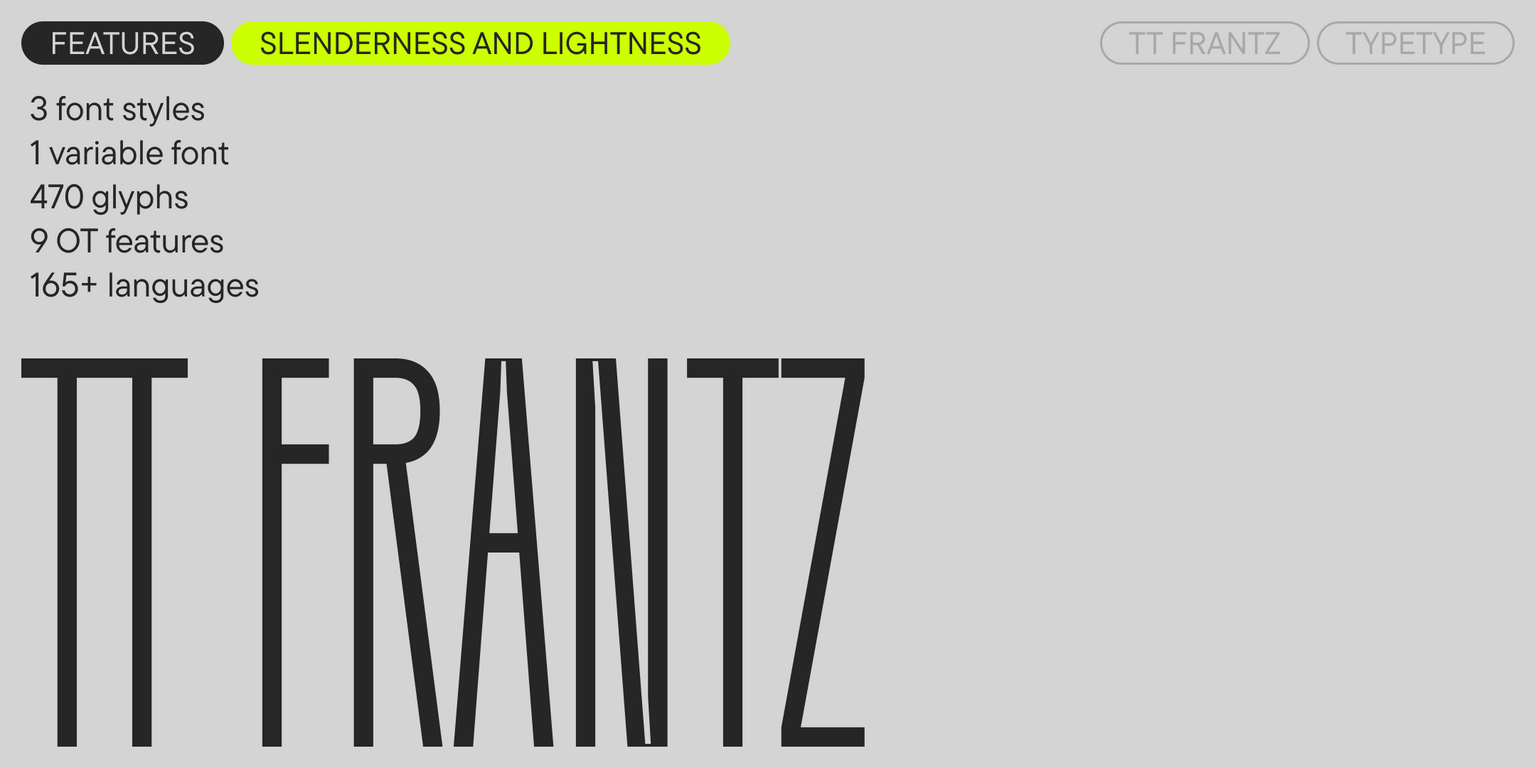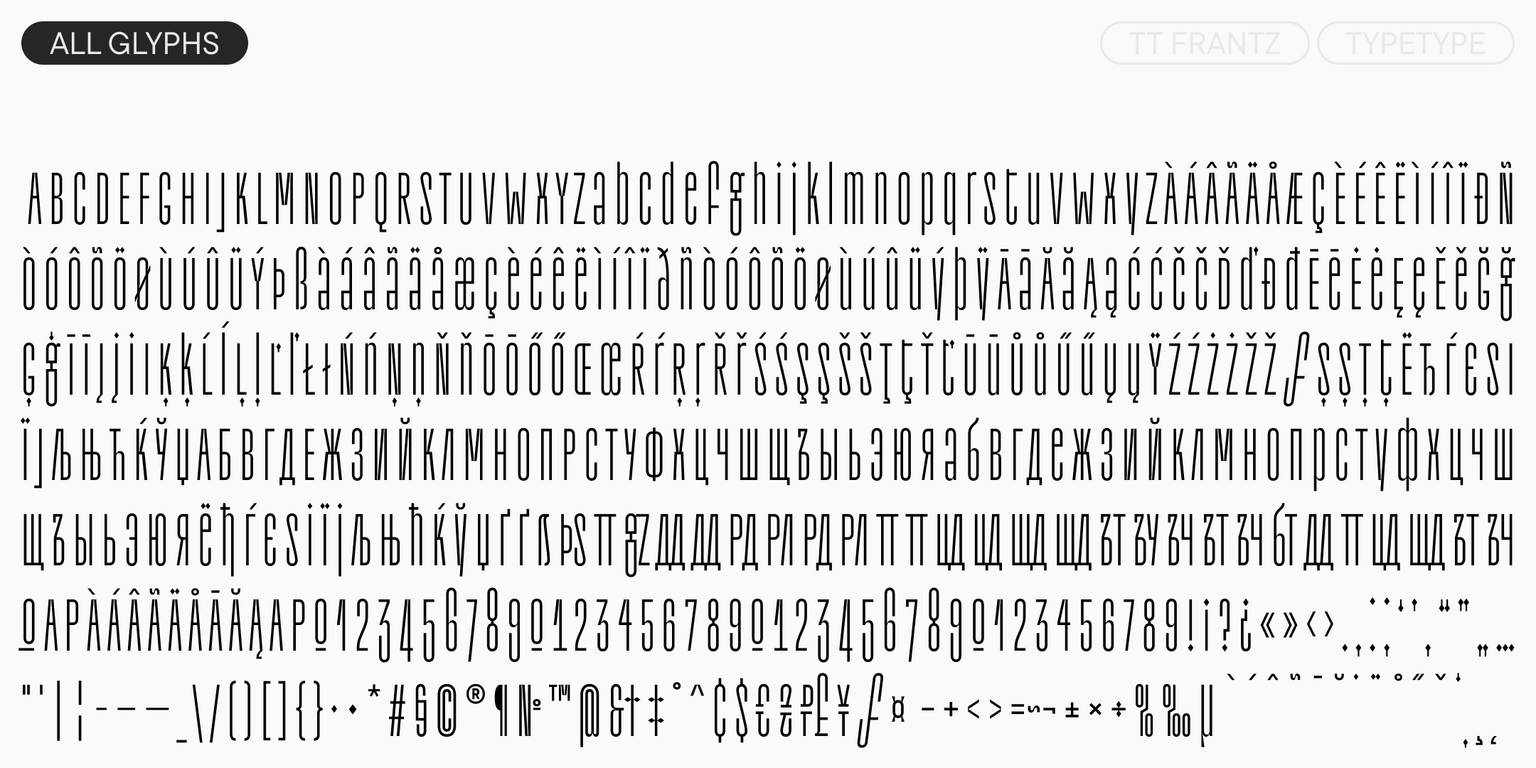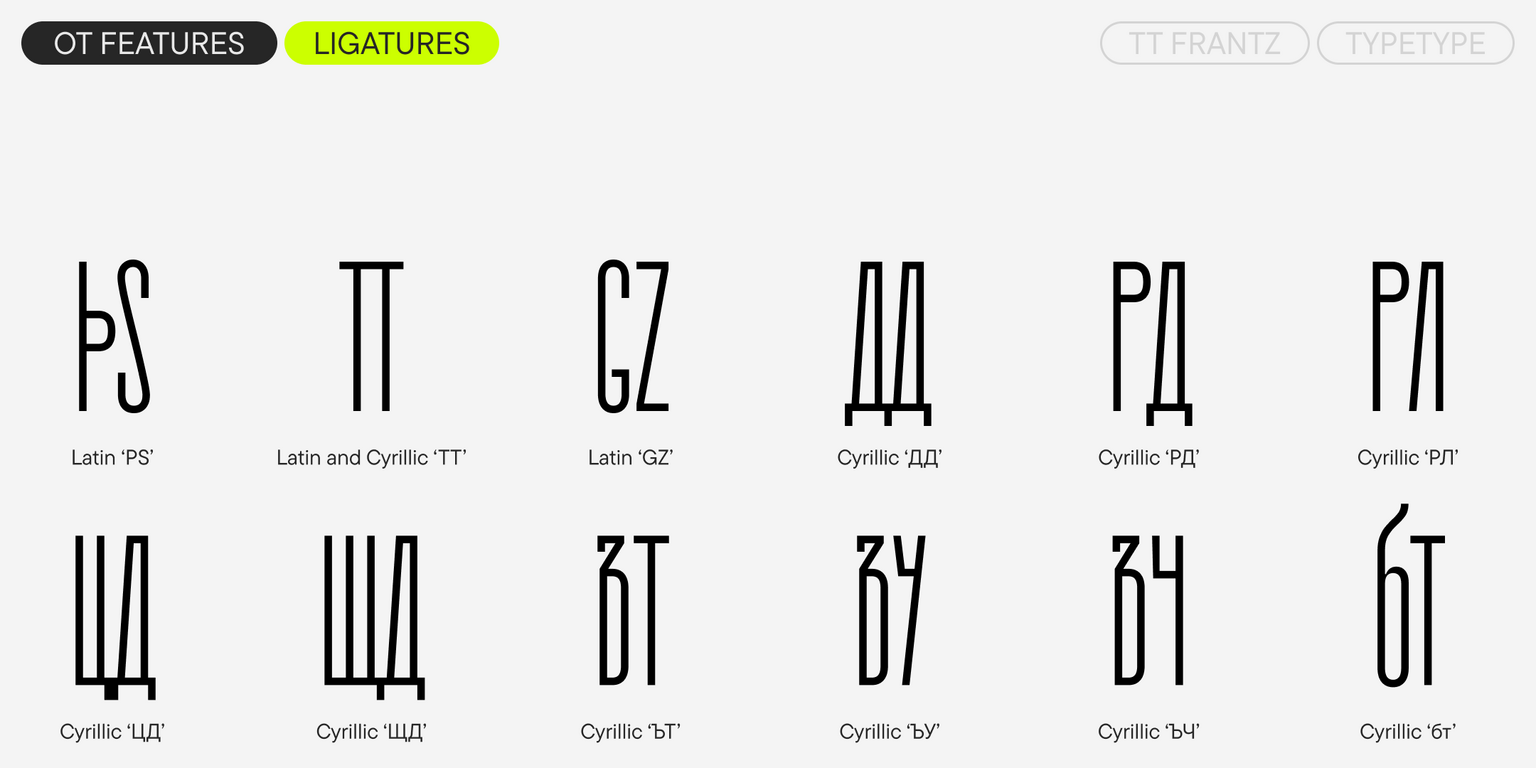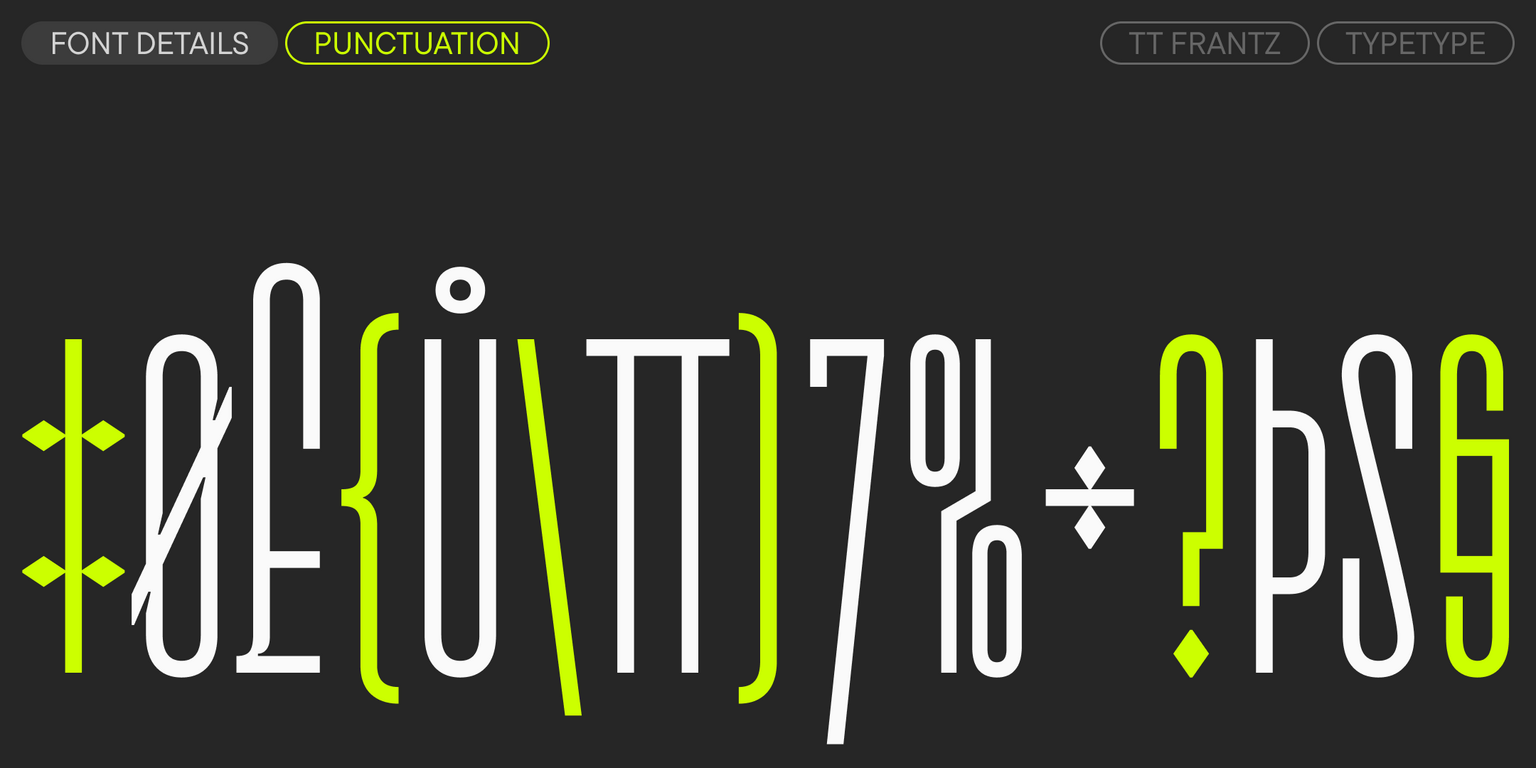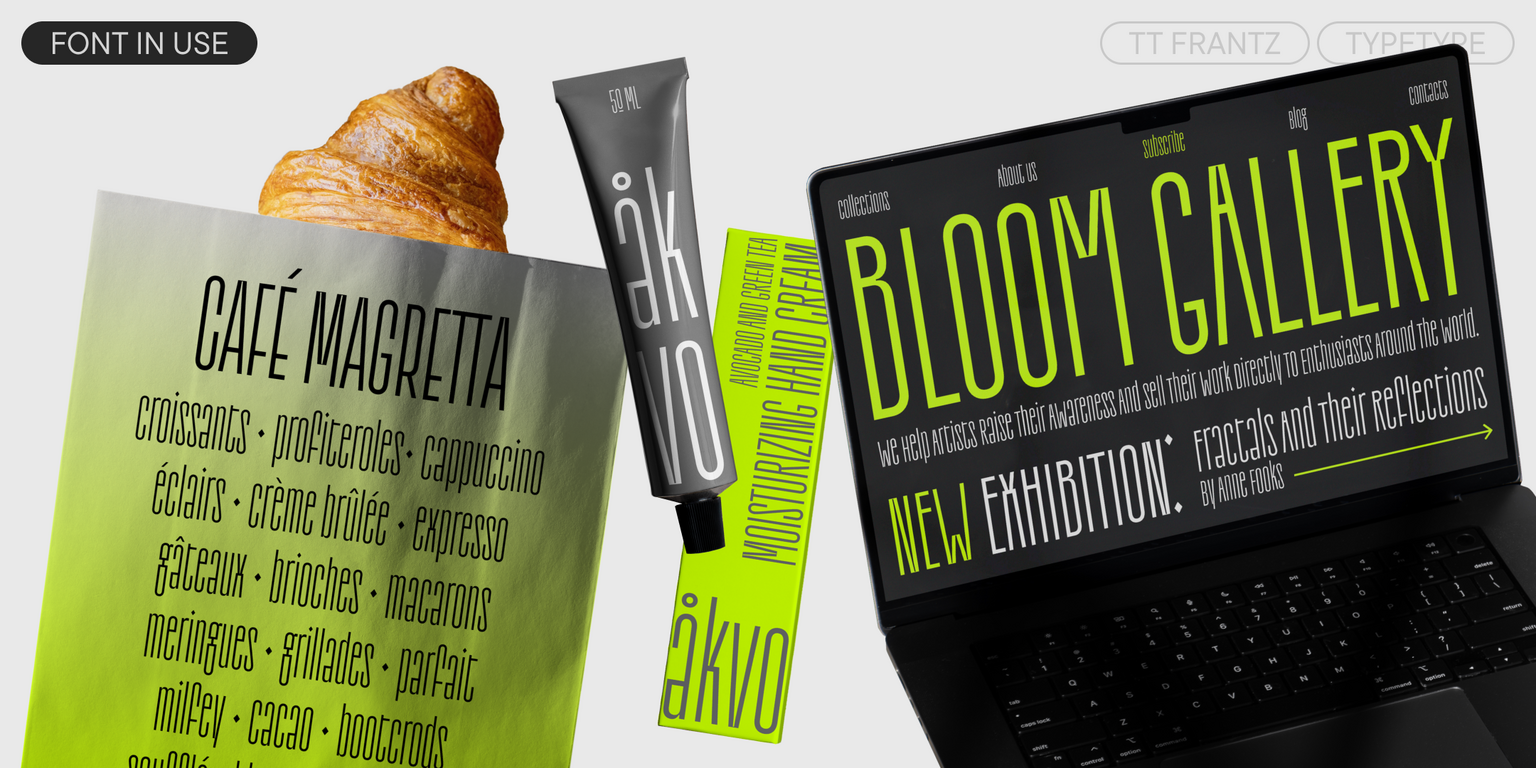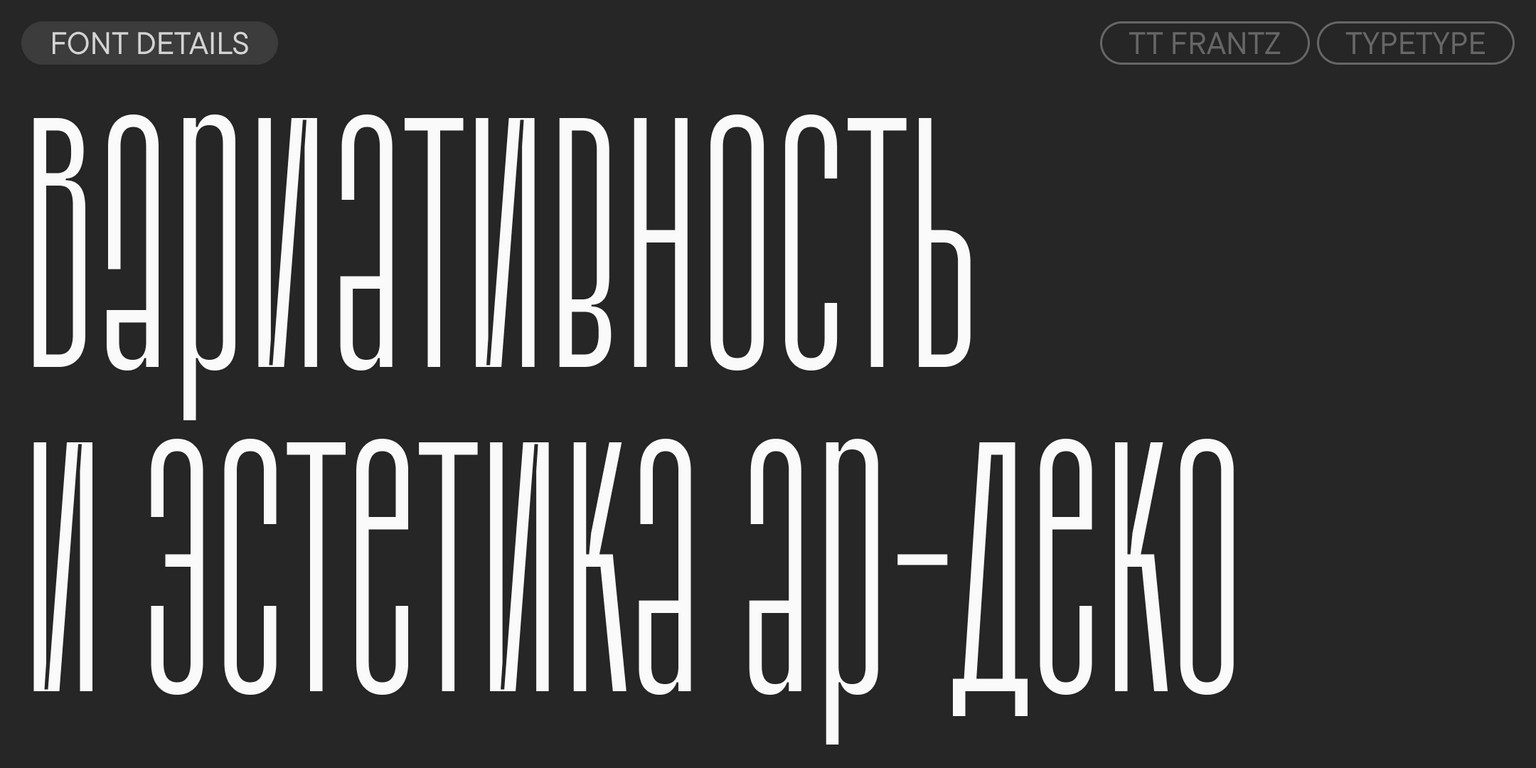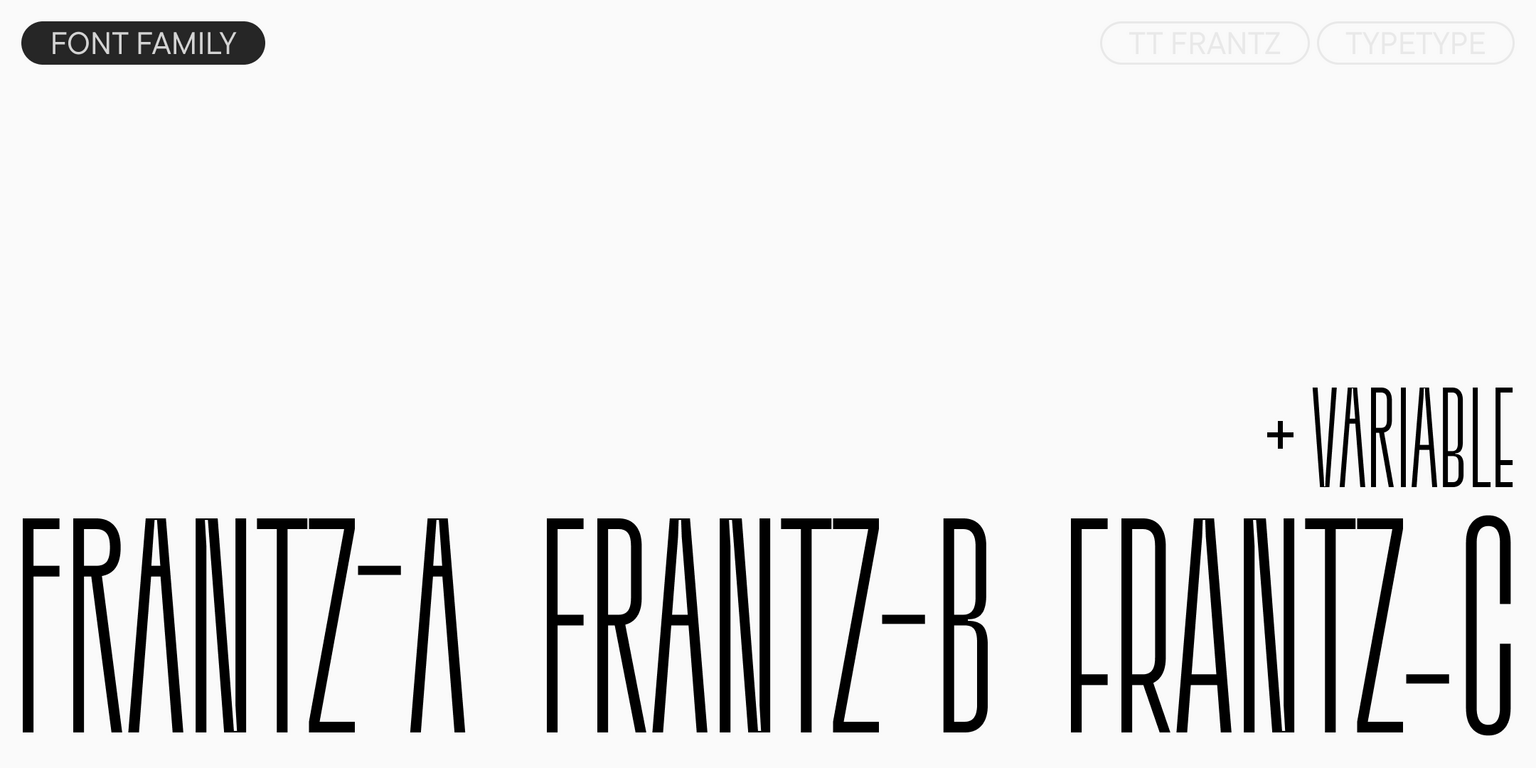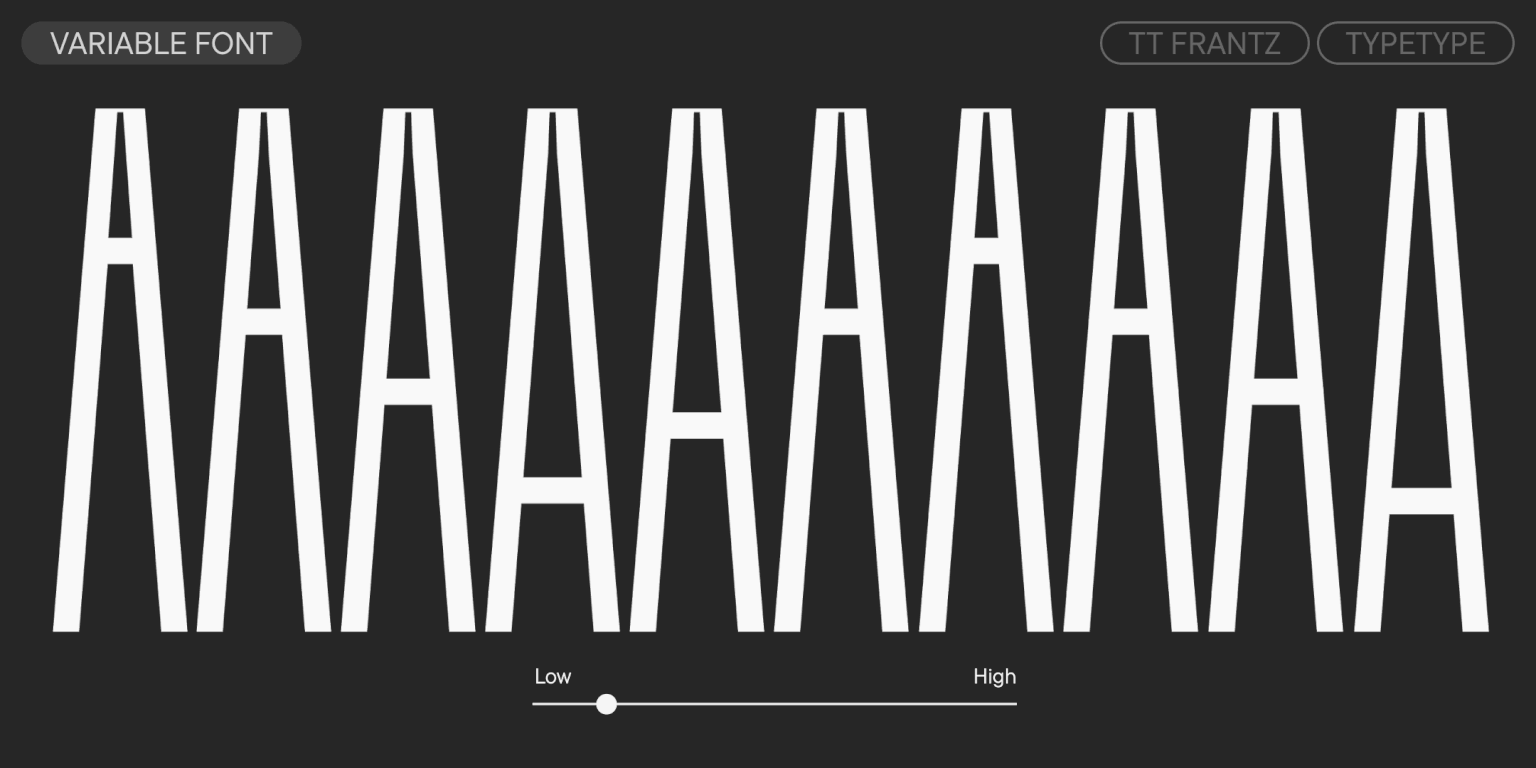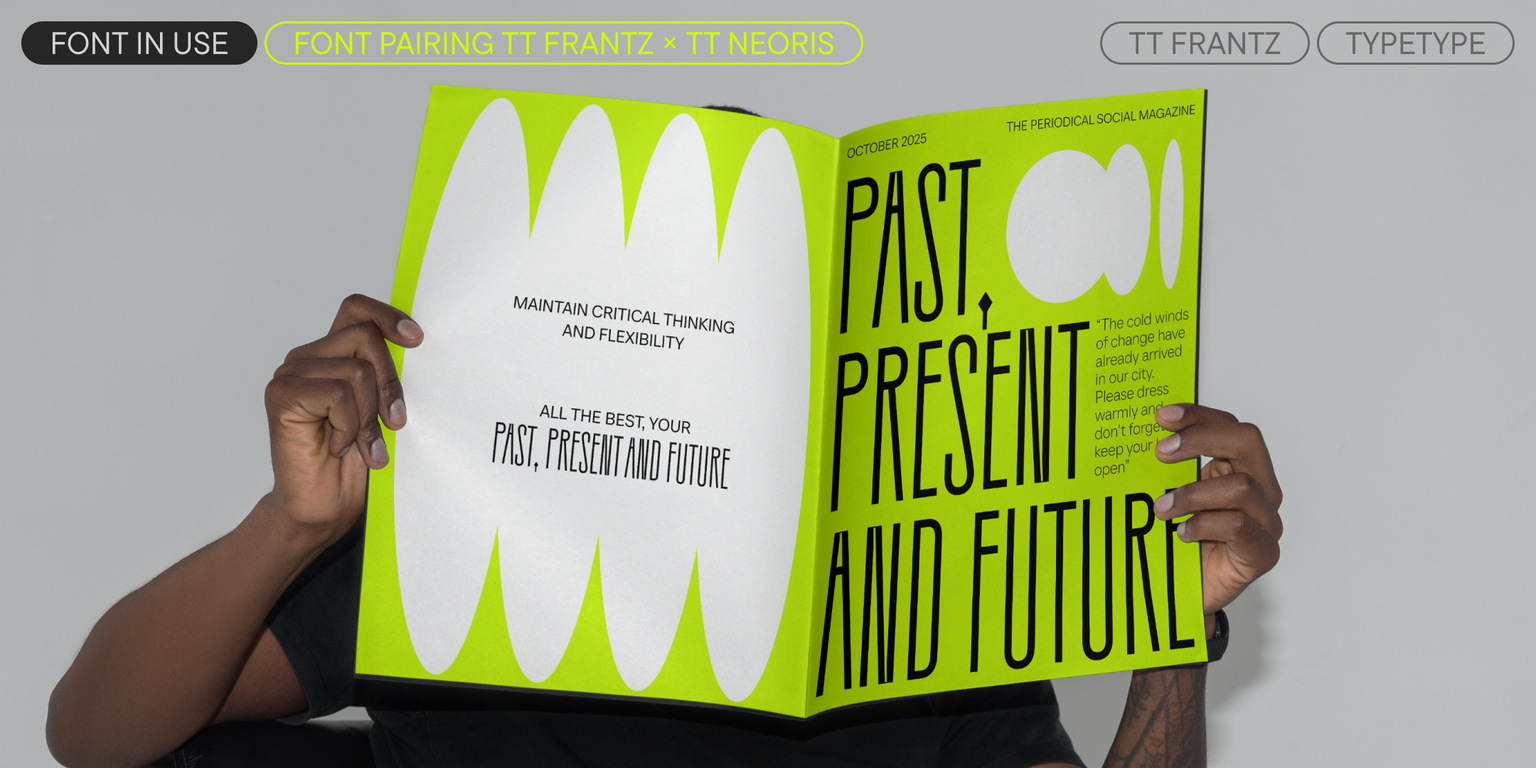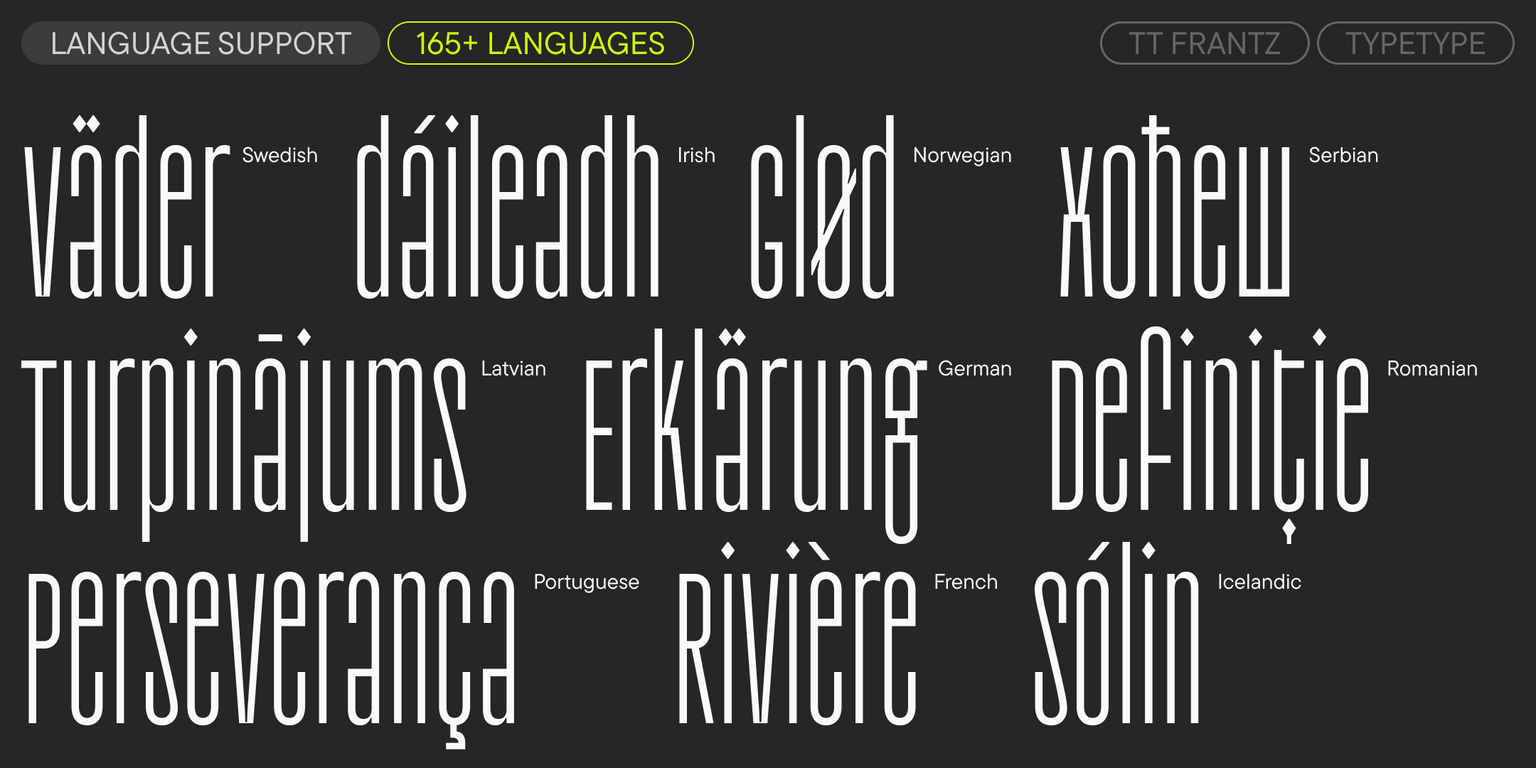
TT Frantz
TT Frantz — ТТ Франтц
Произносится «ТТ Франтц». «Frantz» — имя собственное немецкого происхождения. Буквы «TT» являются аббревиатурой названия компании.
TT Frantz — экспериментальный вариативный шрифт с узкими пропорциями и отсылками к эстетике ар-деко. Высоту средней линии можно регулировать, меняя визуальное восприятие шрифта.
TT Frantz
Вариативный шрифт, выделяющийся своей стройностью и лёгкостью
TT Frantz
В TT Frantz можно найти отсылки в эстетике арт-деко, которые выражены в сильно заниженной или наоборот сильно завышенной талии у букв. Кроме того, в зависимости от положения ползунка регулировки оси, у некоторых букв изменяется закрытость апертуры. Мы постарались сделать так, чтобы при смене вариативности ширина знаков не изменялась, и он оставался моноширинным.
TT Frantz
Вариативность
Display
Мы сделали строчные знаки высотой с прописные, но при этом сохранили небольшие выносные элементы
О гарнитуре TT Frantz
Встречайте TT Frantz версии 1.010!
Обновили знаковый состав нашего шрифта с элементами ар-деко.
TT Frantz — экспериментальный акцидентный гротеск с узкими пропорциями. В нём можно найти небольшие отсылки в эстетике ар-деко, которые выражены в сильно заниженной или, наоборот, сильно завышенной талии у букв. Менять высоту средней линии вы можете самостоятельно благодаря функции вариативности. Кроме того, в зависимости от положения ползунка регулировки оси у некоторых букв меняется степень закрытости апертуры.
Для того, чтобы сохранить основную фишку TT Frantz — изменение высоты средней линии — мы сделали высоту строчных и прописных знаков одинаковой, но при этом сохранили в прописных небольшие выносные элементы. Интересный факт — в кириллических буквах «з», «с», «а», «е» вариативность апертуры идёт по другому сценарию по сравнению с их латинскими собратьями.
При работе над TT Frantz мы сделали так, чтобы при смене вариативности ширина знаков не менялась и пропорции шрифта сохранялись. А ещё мы добавили лигатуры и контекстные альтернативы. Также в гарнитуру входят три отдельных статичных начертания (Frantz A, Frantz B, Frantz C), в каждом из которых средняя линия уже зафиксирована в определённом положении (высоком, среднем и низком).
TT Frantz — декоративный шрифт, который подходит для использования в крупных и средних размерах. Он придаст шарм любому проекту: будет эффектно смотреться в дизайне упаковки косметики и парфюмерии, на обложках журналов о моде и искусстве, на афишах спектаклей и художественных выставок.
TT Frantz 1.010 — это:
• 4 начертания: 3 прямых и 1 вариативный шрифт;
• 470 знаков в каждом начертании;
• 9 OpenType фич;
• Поддержка 165 языков.